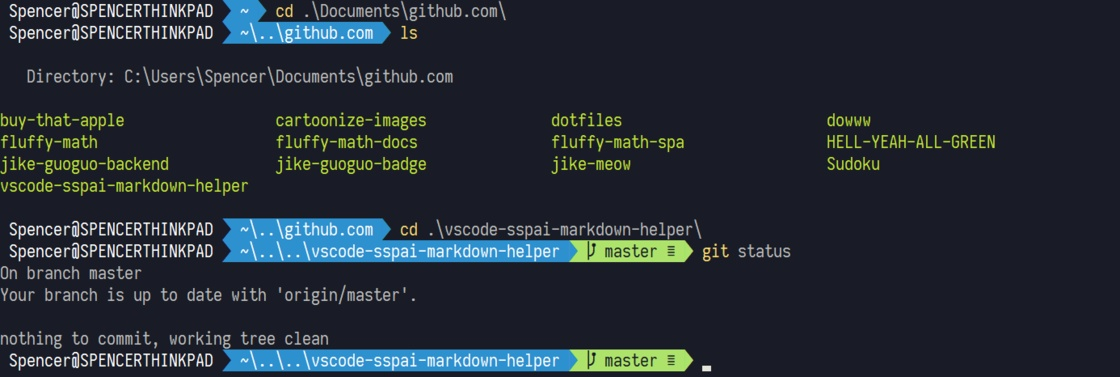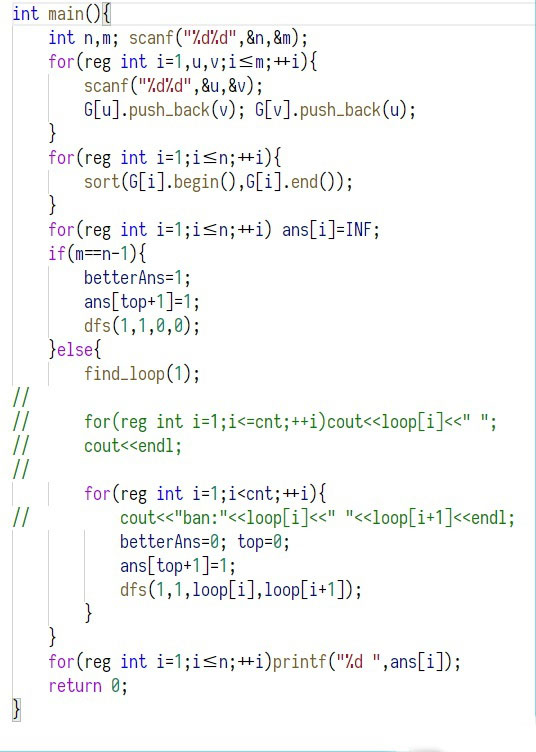
等距更纱黑体, 由 Iosevka 和 思源黑体 组合起来的优秀等宽字体,有着独特的科技风味,很适合在代码编辑、终端以及需要一些科技元素的设计里使用。
等距更纱黑体的西文字符基于 Iosevka 字型设计。
Mono: 等宽字型,全宽破折号。
Term: 等宽字型,半宽破折号。
Fixed: 等宽字型,半宽破折号,无连字。
Slab: 粗衬线体,在原字形基础上增加了 Slab serif 的特征,使其更具有辨识度。
连字 (Ligature) 遇到特定连续的字符时会进行组合,优化阅读体验。在编程语言中,连字特性也能让数学运算符号更容易的阅读。
根据特定语言和地区主要使用的字形来选择字体:SC: 简体中文、TC: 台湾繁体中文、HC: 香港繁体中文、CL: 传统旧字形、J: 日文、K: 韩文。